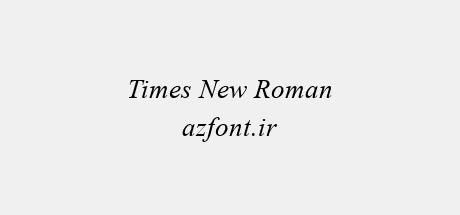
قلم زیبای Times New Roman Italic از سری قلم های بسیار زیبا برای تایپوگرافی و لوگو تایپ می باشد.این قلم در وزن Italic و توسط Monotype Type Drawing Office - Stanley Morison Victor Lardent 1932 طراحی و منتشر شده است.